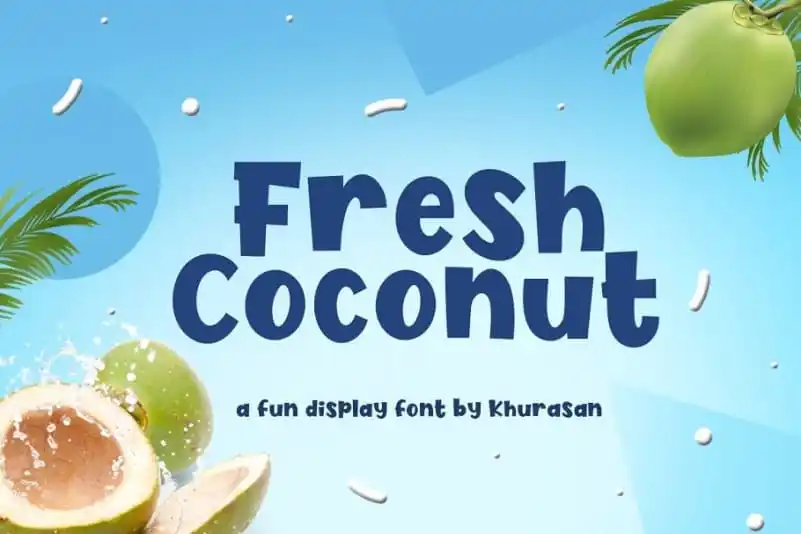
Fresh Coconut Display Font é uma elegante escolha para quem busca uma fonte que transmite alegria e frescura com apenas alguns cliques. Seu design minimalista mas divertido combina perfeitamente com projetos criativos, logos, cartões de aniversário e até mesmo posters. O conjunto completo de letras maiúsculas e minúsculas, conectores, símbolos multilíngues, números e pontuação tornam essa fonte uma opção versátil para qualquer projeto de design que você possa estar planejando. Seu tema alegre é especialmente adaptado para projetos onde um pouco de bom humor pode fazer toda a diferença. Com suporte para várias línguas, Fresh Coconut Display Font é a escolha perfeita para seus clientes multilíngues ou aqueles que desejam criar design em diferentes idiomas. A cada letra, conectora e símbolo você adiciona ao seu projeto, a sensação de frescor vem mais perto de sua ideia final, tornando o processo de criação mais divertido e prazeroso. Seja para um pequeno cartão de aniversário ou uma grande publicidade em outdoors, Fresh Coconut Display Font garante que seu design seja chamativo e memorável. Combinado com os recursos adicionais incluídos, você pode criar designs impactantes sem precisar se preocupar com a legibilidade ou versatilidade da fonte. Além disso, o conjunto completo de letras e símbolos torna fácil integrá-la em um design existente ou mesmo no início de seu próximo projeto. Fresh Coconut Display Font é uma fonte que você pode confiar, não só pelo seu design alegre e versátil, mas também pela sua capacidade de adicionar um toque especial a qualquer trabalho de design.